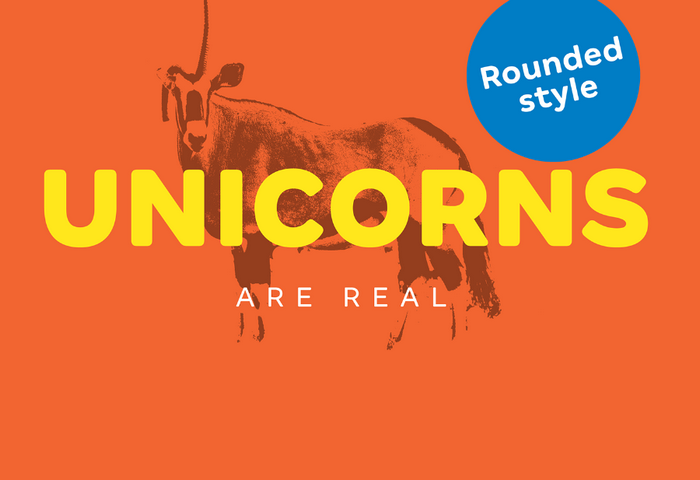
Olá! Estamos muito felizes em apresentar a vocês as melhores fontes para seus projetos de design inovadores. Se está procurando por uma fonte Sans Serif para seu próximo projeto, Margem Font Family será uma excelente escolha. Introduzimos a você o Margem – um conjunto completo de fontes criado pelo Fabio Haag que se adaptam a muitas situações. Margem é uma família de fontes projetada para se encaixar em múltiplos contextos, com sua construção humanista e sans-serif fornecendo uma base sólida para a leitura até os tamanhos mais pequenos. Sobre esta estrutura, formas geométricas introduzem um design contemporâneo que vai ainda mais longe na geometria, incorporando variações estilísticas em letras específicas para destacar no tamanho de visualização. Além disso, uma versão arredondada oferece um sorriso a qualquer mensagem com seus ângulos amigáveis. E finalmente, os itálicos verdadeiros dão vida às todas as variações deste conjunto único e original, resultando em 28 fontes diferentes projetadas para atenderem a qualquer situação. Essa família de fontes é uma ótima opção para tornar seus designers mais versáteis e criativos.